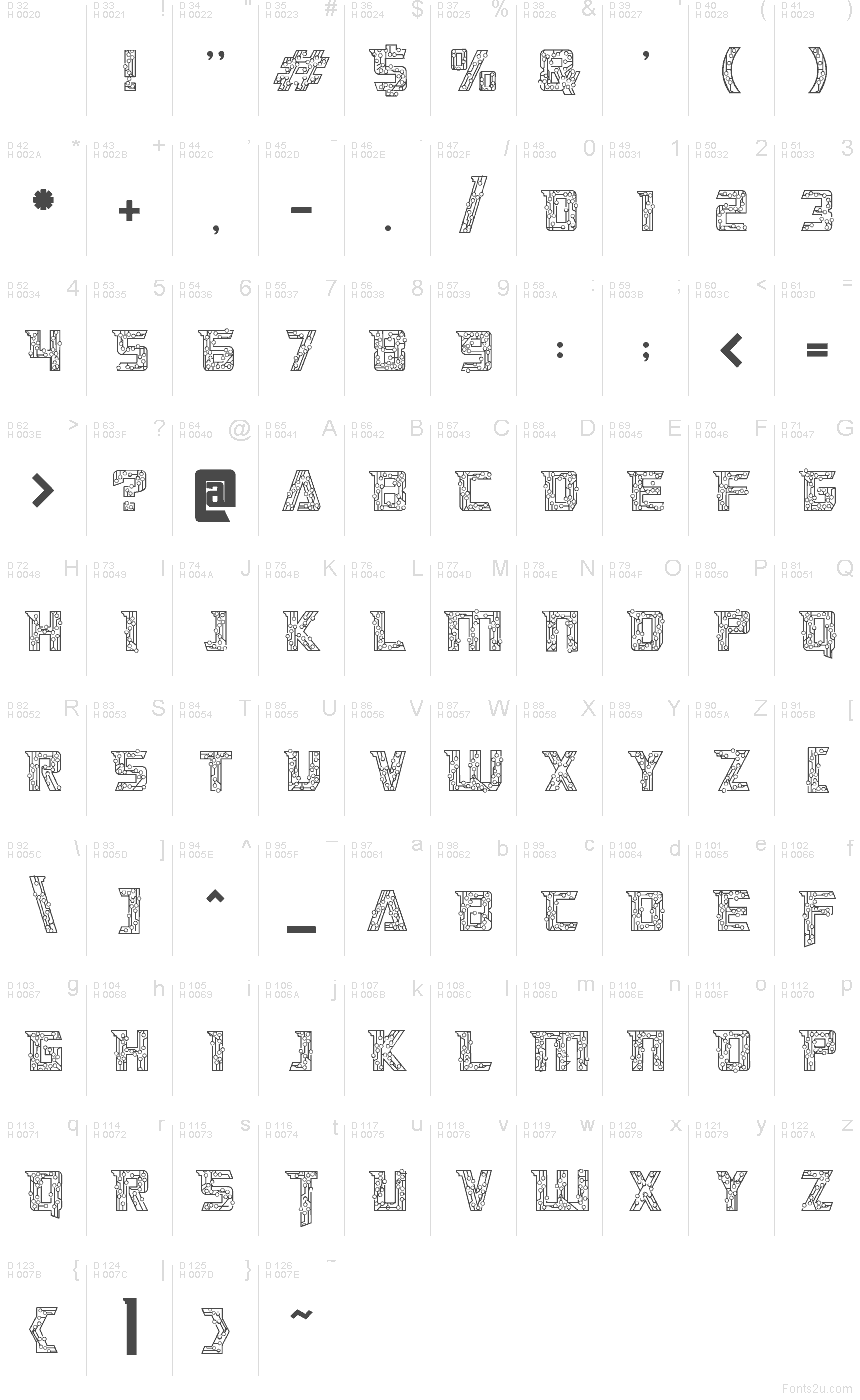
Turbo Type One od Putracetol Studio je bezplatné bezpatkové písmo inspirované plošnými spoji. Čtvercové tvary písmen, protkané tečkami a pravoúhlými spoji, působí jako design elektronických obvodů. Tento opakující se motiv dodává písmu technickou texturu, takže výsledek působí spíše inženýrsky než jen geometricky.
Skvěle vynikne v herních titulech, sci-fi plakátech, grafice technologických akcí, v robotickém brandingu a na obalech inspirovaných rozhraními, kde vzor spojů sám o sobě nese silné sdělení. Nejlépe se uplatní v krátkých nadpisech a logách, protože detaily vnitřního zapojení dodávají každému slovu schematickou hustotu, která by v delším textu zanikla.
Turbo Type One